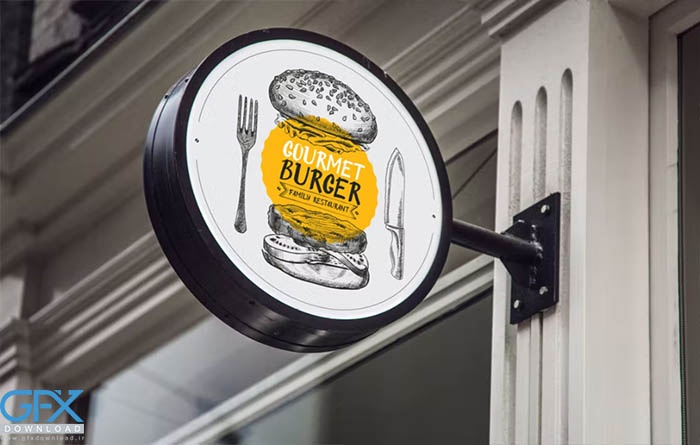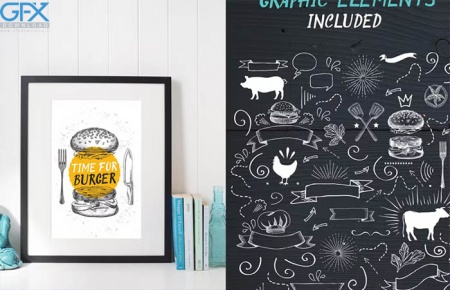
فونت انگلیسی رایگان همبرگر Original Burger
فونت انگلیسی همبرگر Original Burger
دانلود رایگان فونت انگلیسی همبرگر Original Burger
یک فونت طراحی با دست متشکل از حروف بزرگ، علائم نگارشی و اعداد. الفبای پایه لاتین A-Z. همچنین این فونت انگلیسی رایگان با عناصر doodle گرافیکی همراه است. فونت انگلیسی همبرگر Original Burger مناسب برای طراحی منوی رستوران، فست فود و کافه.